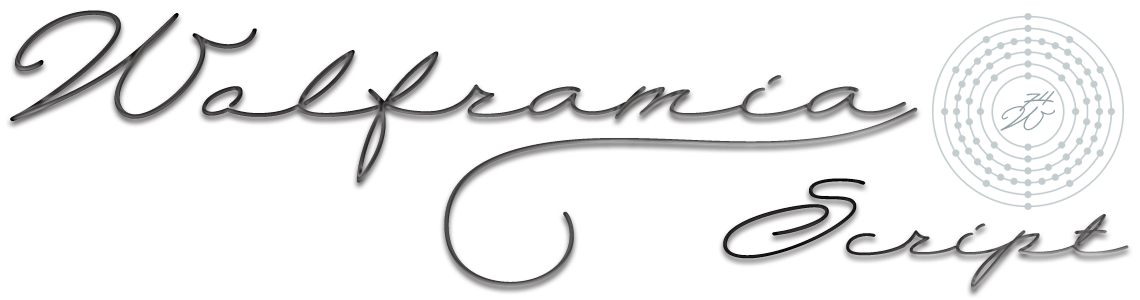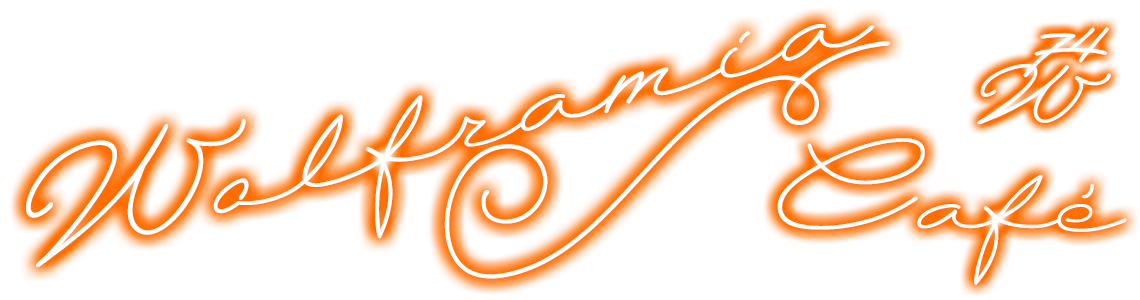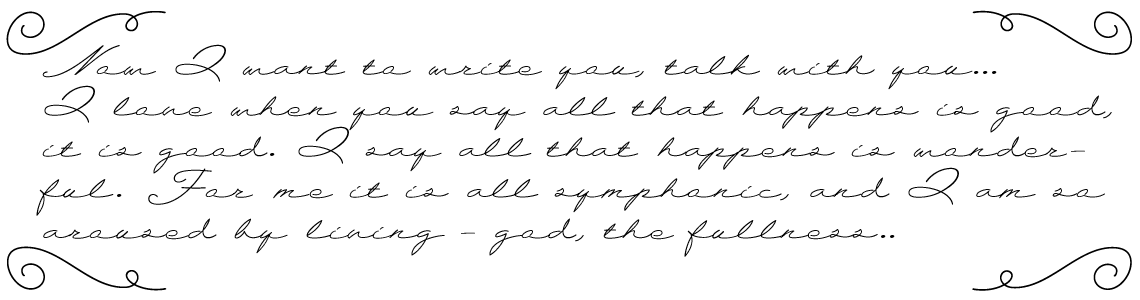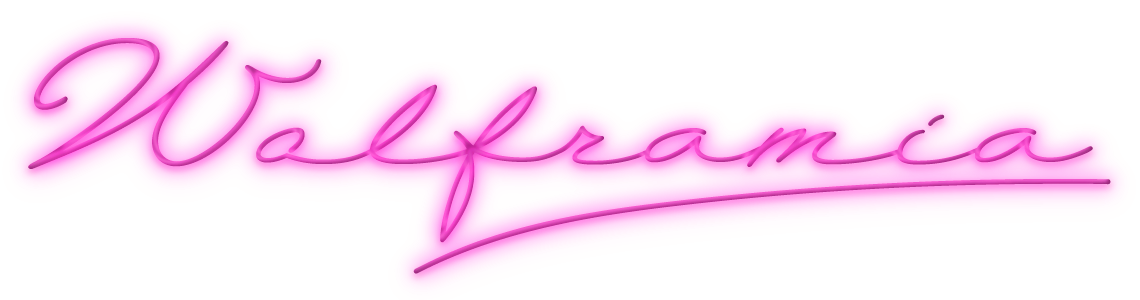
Wolframia es una moderna fuente caligráfica informal concatenada, expandida y redondeada para titulares, invitaciones de todo tipo, felicitaciones o publicidad elegante. Incluye seis ornamentos caligráficos. Latin Extended-A y funciones OpenType. Incluye el símbolo del Bitcoin. El nombre de esta fuente está dedicado al Wolframio conocido en los países de habla inglesa como Tungsteno, número atómico 74. Incluye el símbolo del Bitcoin.
Calligraphic
Estilo: Script, Caligráfica, Manuscrita
Proporción: Expandida
Funciones OpenType: Additional languages, All Alternates, Capital Spacing, Discretionary Ligatures, Fractions, Kerning, Localized Forms, Mathematical Greek, Ordinals, Ornaments, Slashed Zero, Standard Ligatures.
La fuente «Wolframia» dispone en su versión comercial de un juego de 384 glifos (Latin Extended-A), con soporte para cualquier idioma europeo o centro europeo. Wolframia Script también incluye funciones OpenType (Compatibles con InDesign, QuarkXpress, Photoshop, Illustrator y Microsoft Office.